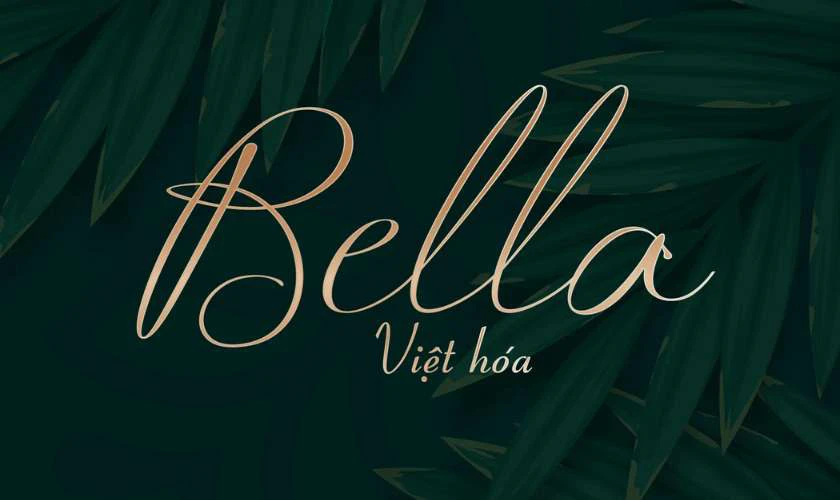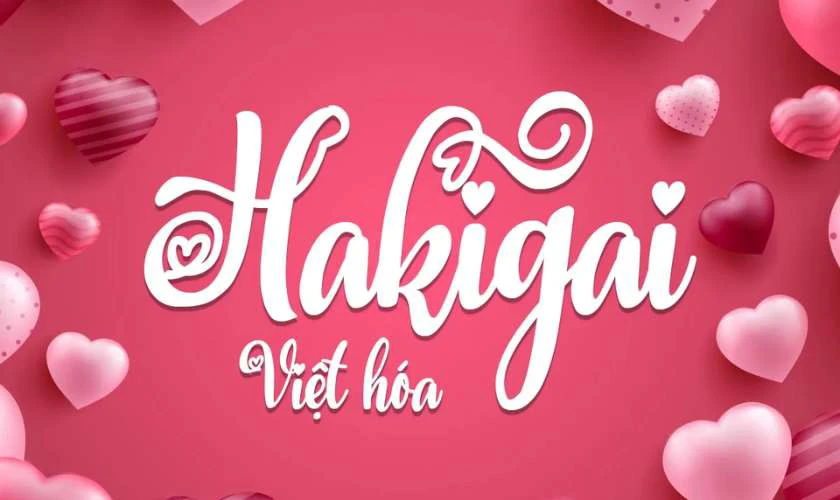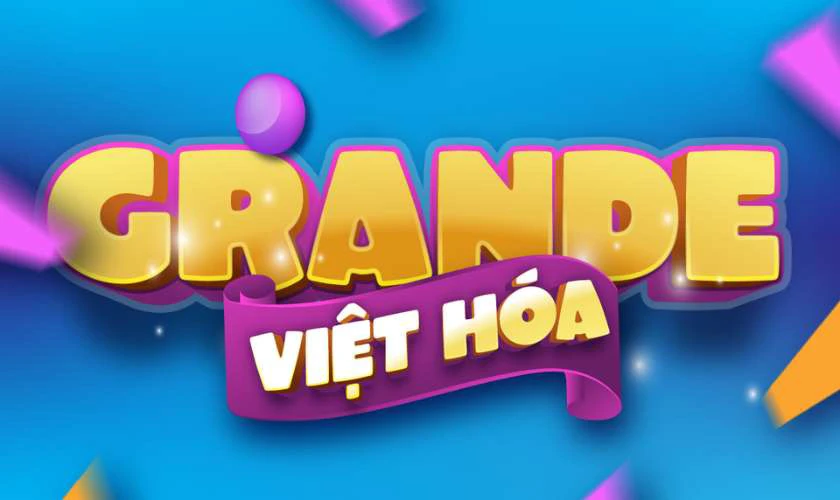
1.000+ font chữ 20/10 Việt hóa đẹp, ấn tượng, miễn phí
Font chữ 20/10 là một yếu tố quan trọng giúp các ấn phẩm thiết kế trở nên độc đáo và ý nghĩa. Việc lựa chọn phông chữ phù hợp sẽ tạo điểm nhấn và truyền tải thông điệp trọn vẹn tới người nhận. Bài viết này sẽ tổng hợp các font chữ dành riêng cho Ngày Phụ nữ Việt Nam 20/10, cùng Điện Thoại Vui theo dõi bạn nhé!
Để tạo nên một tấm thiệp hay poster độc đáo, lựa chọn font chữ 20/10 phù hợp là bước đi đầu tiên vô cùng quan trọng. Các bộ font chữ được Việt hóa mang lại sự tiện lợi cho người dùng. Chúng sẽ giúp bạn dễ dàng gõ các câu chúc có dấu mà không cần cài đặt thêm công cụ hỗ trợ. Dưới đây là danh sách những font chữ được ưa chuộng trong năm 2025 bạn có thể tham khảo.
DVN Lively là một font chữ script mang phong cách vui tươi và năng động. Font chữ này được thiết kế với những đường nét mềm mại nhưng đầy đặn. Điều này tạo nên sự hài hòa giữa sự thanh lịch và nổi bật. Font này đặc biệt ấn tượng với các ký tự tròn trịa, thể hiện sự sáng tạo và linh hoạt.
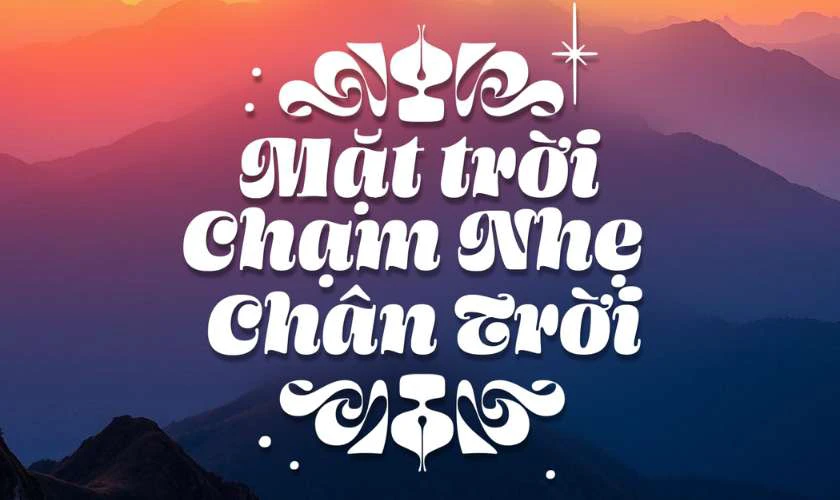
Sử dụng font DVN Lively sẽ làm cho các thiết kế của bạn trở nên tươi mới và đầy cảm hứng. Phông chữ này là một lựa chọn đáng tin cậy để tạo ra những thiết kế đẹp mắt, thu hút người xem.
DVN Astera là một font chữ Serif hiện đại, được Việt hóa và có thiết kế tinh tế. Font chữ mang đến sự hoàn hảo cho các thiết kế cao cấp, sang trọng. Với các đường nét thanh mảnh và mềm mại, DVN Astera kết hợp với các ligature độc đáo. Sự kết hợp này tạo nên một phong cách chữ viết trang nhã và lịch lãm.
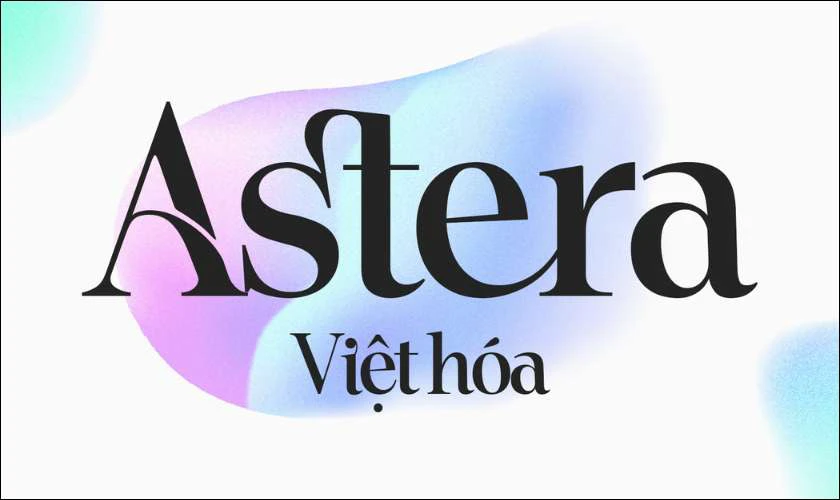
Các ký tự của font chữ này vừa mang nét cổ điển vừa có sự phá cách của thời đại mới. DVN Astera là lựa chọn lý tưởng với những thiết kế mong muốn truyền tải thông điệp sang trọng và đẳng cấp.
Font chữ Arena là sự pha trộn tinh tế giữa phong cách cổ điển và hiện đại. Với các nét đậm, font chữ này thể hiện sự mạnh mẽ nhưng vẫn mềm mại nhờ các đường cong mượt mà. Arena phù hợp cho các dự án thiết kế liên quan đến thương hiệu cao cấp, nơi cần sự sang trọng và sự chuyên nghiệp.
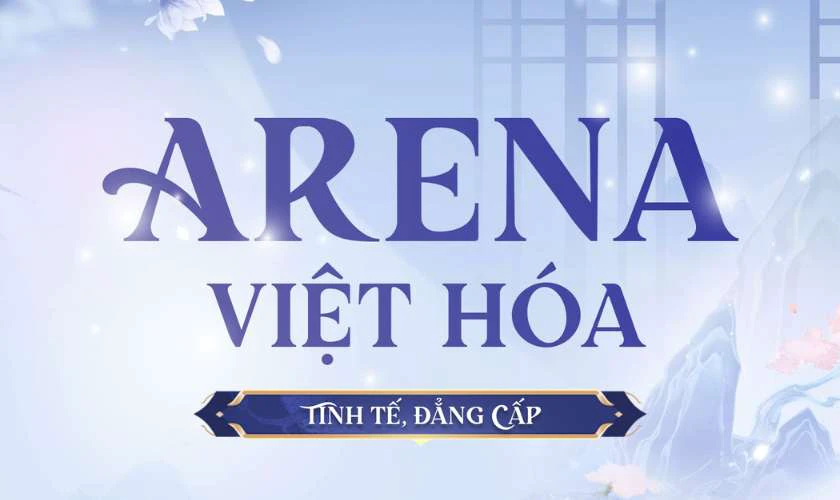
Khoảng cách giữa các chữ cái đã được tối ưu hóa, giúp người đọc dễ dàng tiếp nhận thông tin hơn. Font chữ này là một lựa chọn nên cân nhắc trong ngày 20/10 để tạo ra những thiết kế đẹp mắt, thu hút người xem.
DVN Sophia Beauty là một font chữ lý tưởng cho các thiết kế nữ tính. Ứng dụng đa dạng trong nhiều lĩnh vực: từ thiệp mời, logo, đến các ấn phẩm như bìa sách, tạp chí.
Font chữ này là sự kết hợp hoàn hảo giữa tính cổ điển và sự tinh tế hiện đại. Kết hợp những đường nét mềm mại và mạnh mẽ, tạo ấn tượng mạnh mẽ cho người xem ngay từ cái nhìn đầu tiên.
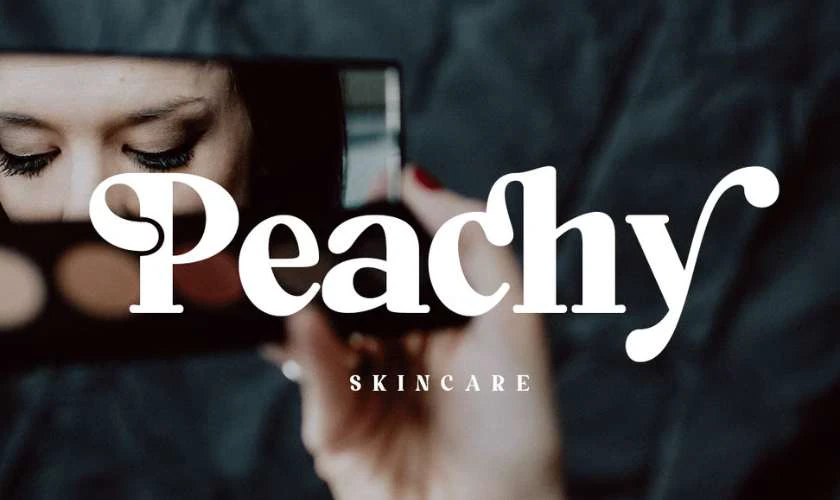
Sự tinh tế và linh hoạt của Sophia Beauty giúp nó dễ dàng tương thích với nhiều phong cách thiết kế khác nhau. Điều này mang lại vẻ đẹp độc đáo và cuốn hút cho bất kỳ dự án nào. Đây là lựa chọn hoàn hảo để thể hiện sự trân trọng và tình cảm sâu sắc.
Shrikhand là một phông chữ Script nét đậm, dày và đầy cá tính. Mặc dù đây là một font chữ Script tuy nhiên các nét chữ dày khá dễ đọc. Font này thể hiện sự mạnh mẽ và gu thẩm mỹ riêng, tạo sự khác biệt và nổi bật.
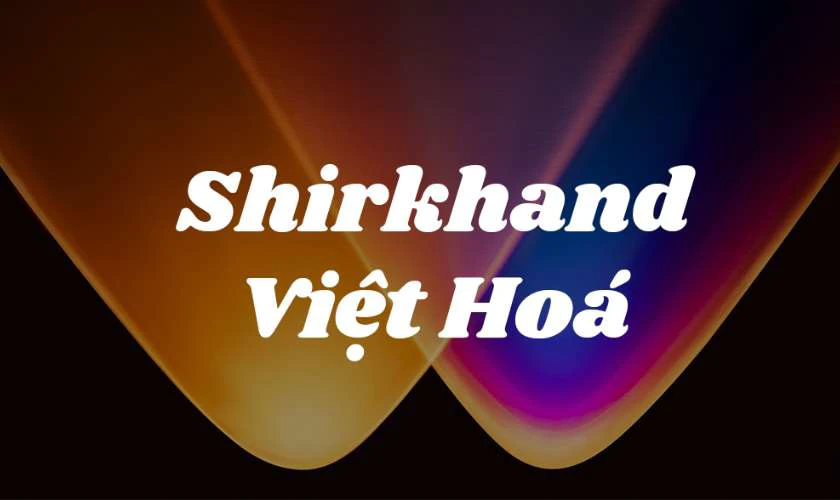
Sự độc đáo trong thiết kế của font này làm cho các ấn phẩm của bạn trở nên khó quên. Đây là lựa chọn hoàn hảo cho những người yêu thích sự phá cách trong các thiết kế của mình.
Những phông chữ này không chỉ đẹp mắt mà còn rất đa dạng về phong cách. Bạn có thể sử dụng những bộ font này để làm thiệp mời, banner quảng cáo hoặc các thiết kế mạng xã hội.
Mỗi font chữ mang một dấu ấn riêng, giúp bạn thỏa sức thể hiện cá tính và sáng tạo trong từng thiết kế. Hãy khám phá và lựa chọn những kiểu chữ phù hợp nhất để tạo nên những tác phẩm nghệ thuật đầy ý nghĩa bạn nhé!
Những font chữ viết tay nét thanh nét đậm là một lựa chọn vô cùng hoàn hảo với chủ đề 20/10. Những phông chữ này mô phỏng nét bút thư pháp tinh tế của người xưa, mang lại sự sang trọng và lãng mạn. Chúng thường được dùng để thiết kế thiệp mời, thiệp chúc mừng, hoặc các tác phẩm mang tính nghệ thuật cao.
Những kiểu chữ này tạo cảm giác gần gũi, chân thực và đầy hoài niệm. Dưới đây là một số font chữ 20/10 viết tay nét thanh nét đậm, truyền thống.
DVN Loveya Script là một font chữ script mang vẻ đẹp tinh tế và lãng mạn, với các đường nét uốn lượn mềm mại. Điều này tạo nên cảm giác liền mạch và duyên dáng. Điểm đặc biệt của font chữ là các họa tiết hình trái tim được lồng ghép tinh tế vào những nét nối. Chi tiết này làm nổi bật phong cách thanh thoát và đầy nữ tính, tạo nên cảm giác quen thuộc.
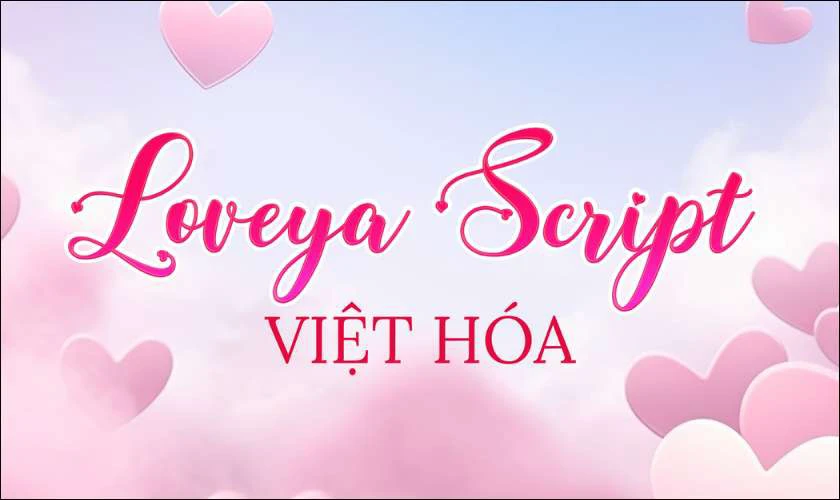
Lựa chọn DVN Loveya Script là cách để bạn gửi gắm những thông điệp yêu thương một cách tinh tế. Phông chữ này là một công cụ hoàn hảo để bạn thể hiện tình cảm chân thành và sự trân trọng đến người phụ nữ.
Lấy cảm hứng từ phong cách thư pháp cổ điển và trang nhã, Peristiwa Script là một phông chữ độc đáo. Nét viết tay hoàn hảo với góc vuông đậm là sự lựa chọn hoàn hảo cho thiệp mời đám cưới và thiệp chúc mừng. Phông chữ này mang lại cảm giác sang trọng và đầy nghệ thuật.